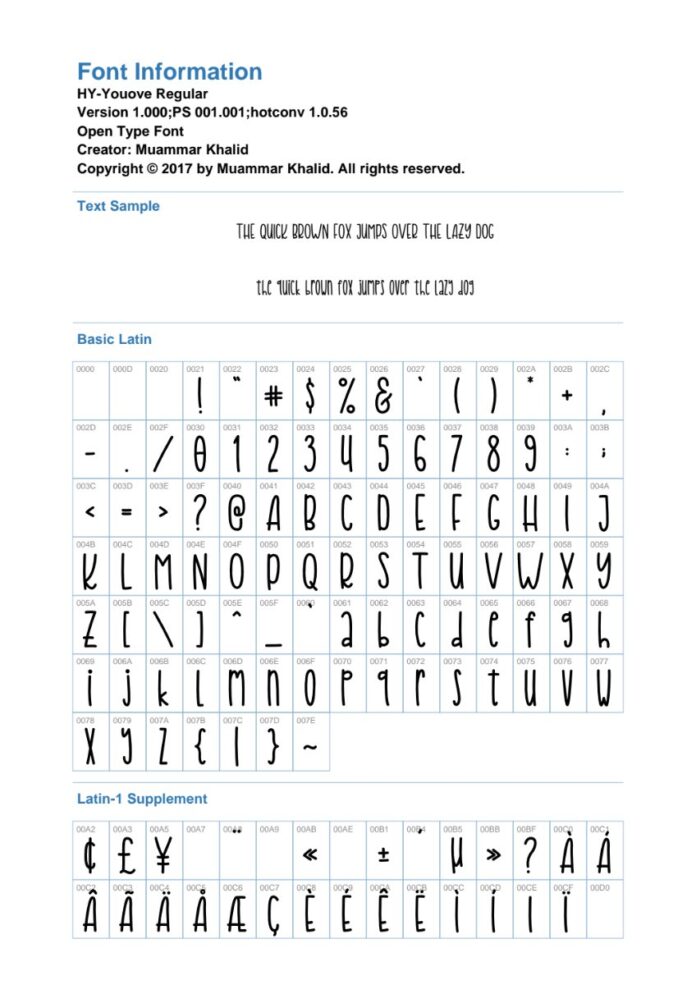
Font chữ HY-Youove độc đáo
Font chữ HY-Youove độc đáo. Khám phá font chữ HY-Youove, một lựa chọn tuyệt vời cho các thiết kế cần sự độc đáo và cá tính. Font chữ này mang đến vẻ ngoài viết tay tự nhiên, phù hợp cho nhiều dự án sáng tạo, từ tiêu đề đến các ấn phẩm nghệ thuật. Tải ngay tại Poster.vn!
Trong thế giới thiết kế đồ họa đầy cạnh tranh, việc lựa chọn một font chữ phù hợp có thể tạo nên sự khác biệt lớn cho tác phẩm của bạn. Font chữ HY-Youove là một lựa chọn không thể bỏ qua nếu bạn đang tìm kiếm sự độc đáo, cá tính và một chút nét viết tay tự nhiên. Với thiết kế đặc biệt, HY-Youove hứa hẹn sẽ thổi hồn vào mọi dự án của bạn.
Giới thiệu về Font chữ HY-Youove
HY-Youove là một font chữ thuộc kiểu chữ viết tay (handwritten font) với các nét chữ được thiết kế phóng khoáng, tự nhiên và đầy ngẫu hứng. Điều này tạo nên một cảm giác gần gũi, thân thiện nhưng không kém phần nghệ thuật. Font chữ này rất phù hợp cho các thiết kế muốn truyền tải sự sáng tạo, cá tính và không theo khuôn mẫu.
Với bộ ký tự đầy đủ bao gồm chữ hoa, chữ thường, số và các ký tự đặc biệt, HY-Youove mang lại sự linh hoạt cao trong việc sử dụng. Từ các tiêu đề nổi bật đến những đoạn văn ngắn cần sự nhấn nhá, font chữ này đều có thể đáp ứng một cách xuất sắc.
Đặc điểm nổi bật của Font HY-Youove
• Phong cách viết tay độc đáo: Mỗi ký tự đều được thiết kế tỉ mỉ, mô phỏng nét viết tay chân thực, tạo cảm giác thủ công và cá nhân hóa.
• Tính linh hoạt cao: Phù hợp với nhiều loại hình thiết kế khác nhau, từ in ấn đến kỹ thuật số.
• Dễ đọc: Mặc dù mang phong cách viết tay, HY-Youove vẫn đảm bảo tính dễ đọc, giúp thông điệp của bạn được truyền tải rõ ràng.
• Tạo điểm nhấn ấn tượng: Với sự độc đáo của mình, font chữ này giúp các thiết kế của bạn trở nên nổi bật và thu hút ánh nhìn.
Ứng dụng của Font chữ HY-Youove trong thiết kế
Font chữ HY-Youove có thể được ứng dụng rộng rãi trong nhiều lĩnh vực thiết kế khác nhau, mang lại hiệu quả thẩm mỹ cao:
Thiết kế thương hiệu và logo
Nếu bạn đang xây dựng một thương hiệu trẻ trung, năng động, hoặc có tính nghệ thuật cao, HY-Youove là một lựa chọn tuyệt vời cho logo và bộ nhận diện thương hiệu. Nét chữ độc đáo sẽ giúp thương hiệu của bạn dễ dàng được nhận diện và ghi nhớ.
Thiết kế poster, banner và quảng cáo
Với khả năng tạo điểm nhấn mạnh mẽ, HY-Youove rất lý tưởng cho các tiêu đề trên poster, banner, hoặc các ấn phẩm quảng cáo. Nó sẽ thu hút sự chú ý của người xem ngay từ cái nhìn đầu tiên, đặc biệt là trong các chiến dịch quảng cáo sáng tạo hoặc sự kiện nghệ thuật.
Thiết kế thiệp mời, thiệp chúc mừng
Sự ấm áp và cá nhân hóa của HY-Youove rất phù hợp để thiết kế thiệp mời sinh nhật, thiệp cưới, thiệp chúc mừng hoặc các ấn phẩm mang tính cá nhân khác. Nó sẽ làm cho thông điệp của bạn trở nên chân thành và đặc biệt hơn.
Thiết kế bao bì sản phẩm
Đối với các sản phẩm thủ công, sản phẩm tự nhiên, hoặc các mặt hàng hướng đến đối tượng trẻ, HY-Youove có thể giúp tạo ra một thiết kế bao bì độc đáo, thân thiện và thu hút.
Thiết kế sách, tạp chí và blog
Trong các ấn phẩm in ấn hoặc kỹ thuật số như sách, tạp chí, blog, font chữ này có thể được sử dụng cho tiêu đề chương, trích dẫn nổi bật hoặc các phần đặc biệt để tạo sự khác biệt và thu hút người đọc.
Cách sử dụng Font chữ HY-Youove hiệu quả
Để tối ưu hóa hiệu quả khi sử dụng font HY-Youove, bạn có thể tham khảo một số mẹo sau:
• Kết hợp với font chữ đơn giản: Vì HY-Youove đã rất nổi bật, hãy kết hợp nó với một font chữ sans-serif hoặc serif đơn giản, dễ đọc cho phần nội dung chính để tạo sự cân bằng và hài hòa.
• Sử dụng cho tiêu đề và điểm nhấn: Font chữ này phát huy tối đa vẻ đẹp khi được dùng cho các tiêu đề, slogan, hoặc các đoạn văn ngắn cần sự chú ý.
• Lựa chọn màu sắc phù hợp: Tùy thuộc vào phong cách thiết kế, bạn có thể sử dụng HY-Youove với màu sắc tươi sáng để tăng tính năng động, hoặc màu sắc trầm hơn để tạo vẻ cổ điển, nghệ thuật.
• Điều chỉnh khoảng cách chữ (kerning) và dòng (leading): Đôi khi, việc điều chỉnh nhỏ các thông số này có thể giúp font chữ trông đẹp và dễ đọc hơn, đặc biệt là khi sử dụng ở kích thước lớn.